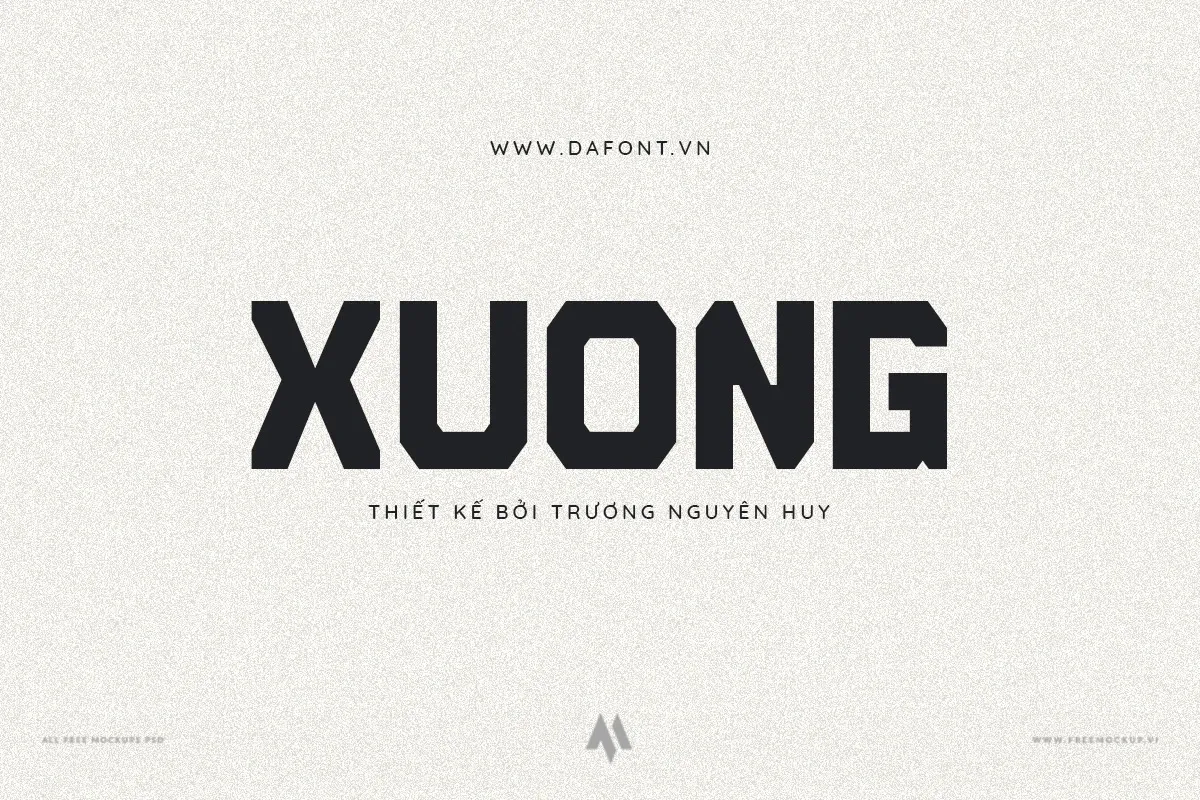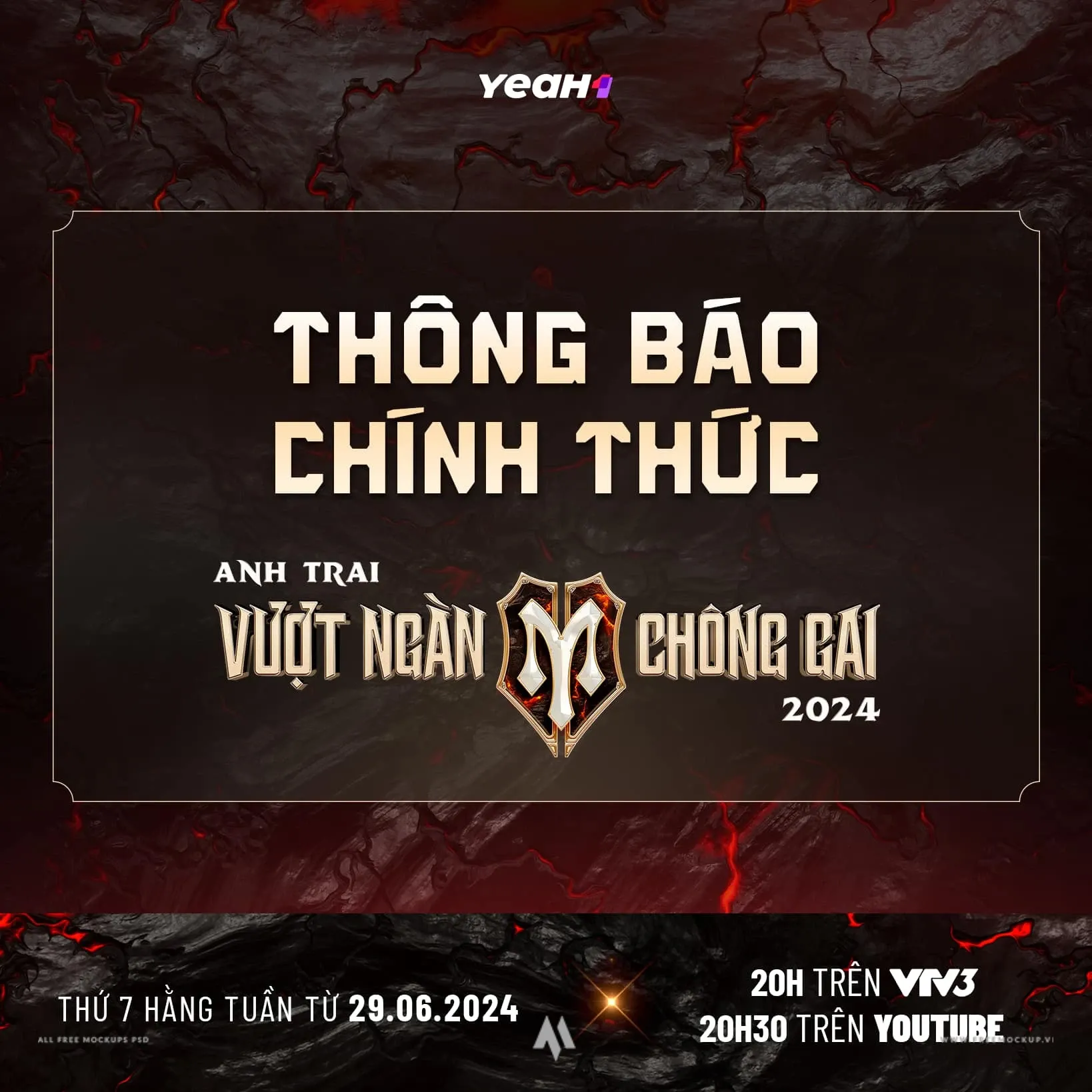
Xuong Display Typeface là bộ font chữ hiển thị (Display Font) độc đáo được thiết kế bởi Trương Nguyên Huy, lấy cảm hứng từ hình tượng Xuồng Ba Lá – phương tiện di chuyển mộc mạc gắn liền với đời sống sông nước miền Tây Nam Bộ. Với cấu trúc chữ in hoa toàn bộ (All-Caps) vững chãi, bộ font tái hiện sinh động kỹ thuật ghép ván gỗ thủ công, mang đậm bản sắc văn hóa Việt và từng tạo dấu ấn mạnh mẽ trong chương trình truyền hình thực tế Anh trai vượt ngàn chông gai.
Đặc điểm nổi bật
- Cảm hứng văn hóa miền Tây: Từng nét chữ mô phỏng cấu trúc ba mảnh ván phẳng chắc chắn của xuồng ba lá, đem lại cảm giác mộc mạc, đậm chất thủ công và chiều sâu văn hóa.
- Định dạng All-Caps mạnh mẽ: Toàn bộ hệ thống ký tự được thiết kế dạng chữ hoa nổi bật, tối ưu cho các tiêu đề lớn, bảng hiệu và yếu tố trang trí thị giác.
Ứng dụng đa dạng trong thiết kế
- Truyền thông & Show giải trí: Visual chương trình truyền hình, poster gameshow, banner quảng bá sự kiện âm nhạc và nghệ thuật biểu diễn.
- Dự án văn hóa & Du lịch: Ấn phẩm quảng bá du lịch sông nước miền Tây, bìa sách văn hóa dân gian, poster triển lãm và phim tư liệu.
- Nhận diện thương hiệu: Thiết kế logo, bảng hiệu nhà hàng món Việt, quán cafe phong cách retro/mộc, thương hiệu thời trang địa phương và quà lưu niệm.
- Bao bì & Nhãn mác: Bao bì đặc sản vùng miền, nhãn mác sản phẩm thủ công truyền thống và hộp quà tết mang phong vị quê hương.